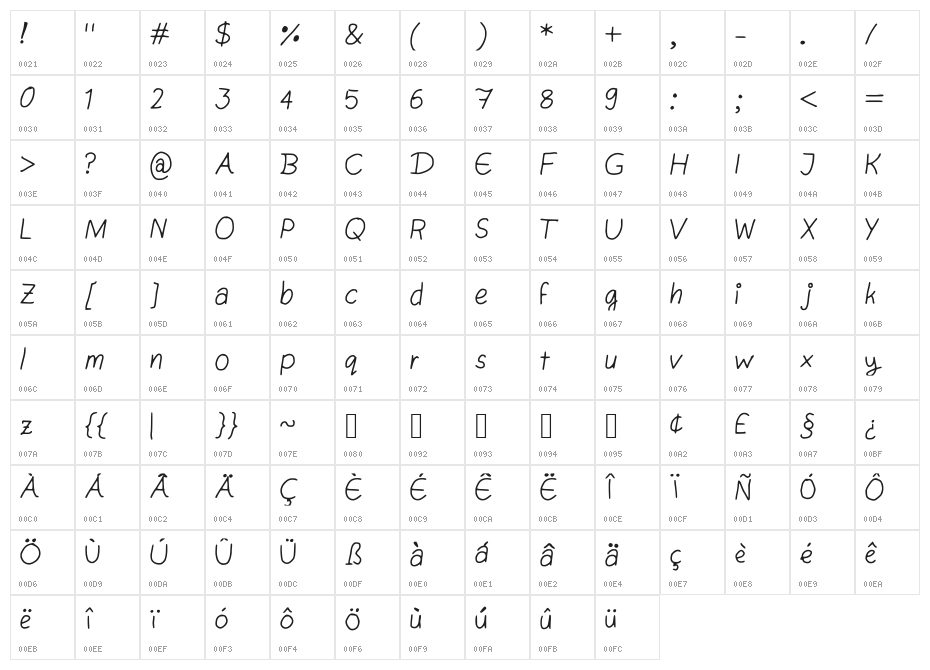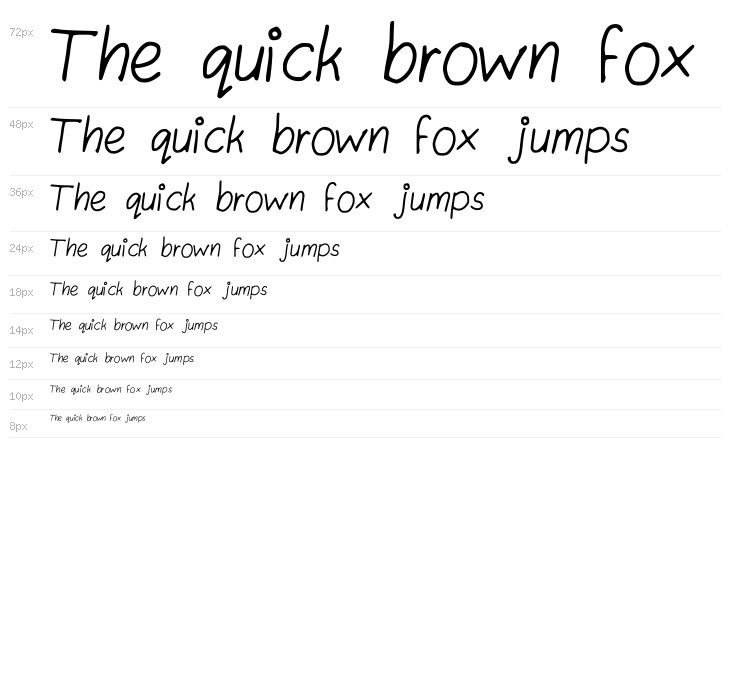
Swirl_ Font
| Gesamtstil | Playful, Casual, Whimsical |
| Anwendungsfall | Headlines, Invitations, Creative projects |
| Vorgeschlagene Projekte | Greeting cards, children's books, creative invitations, personal branding, and playful logos. |